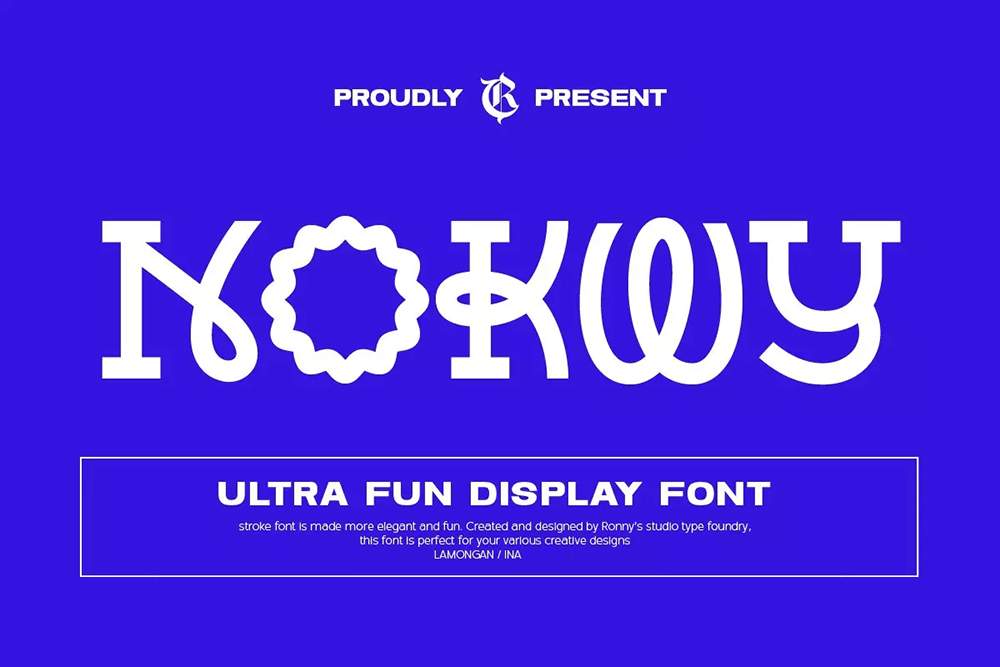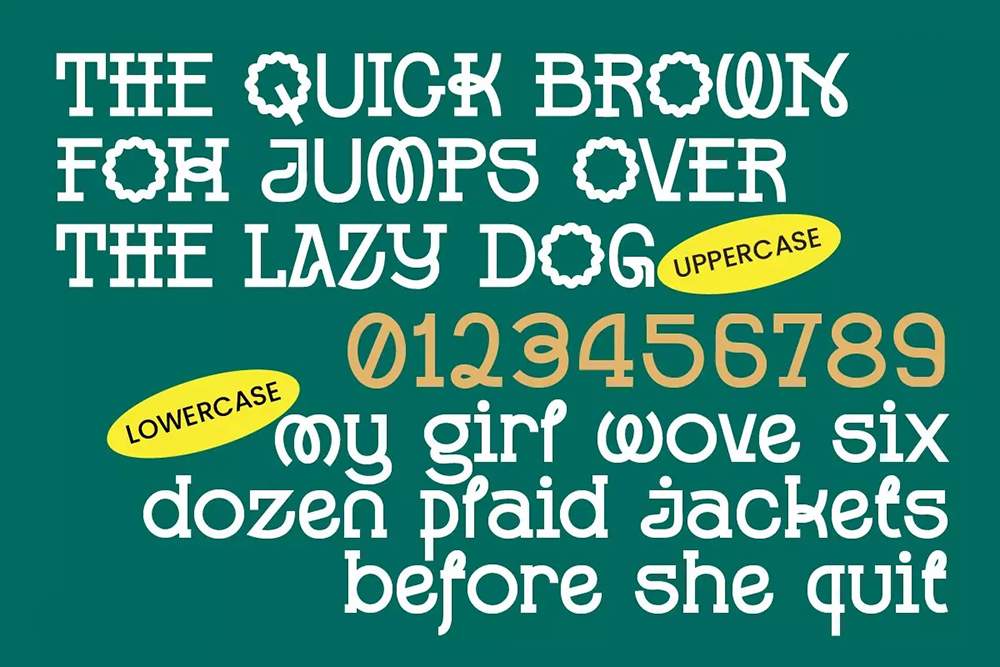
فونت پرمیوم و انگلیسی Nokwy Font یک فونت نمایشی منحصر به فرد است که برای انواع نمایش و برندسازی معاصر عالی است. این فونت دارای فونتهایی است…
فونت پرمیوم و انگلیسی Nokwy Font یک فونت نمایشی منحصر به فرد است که برای انواع نمایش و برندسازی معاصر عالی است. این فونت دارای فونتهایی است که به اندازه کافی جذاب هستند تا خوانندگان را جذب کنند و لبخند را بر لبانشان بنشانند. این فونت بسیار ساده و چشمنواز به نظر میرسد.
مزایای استفاده از فونت لاتین Nokwy چیست؟